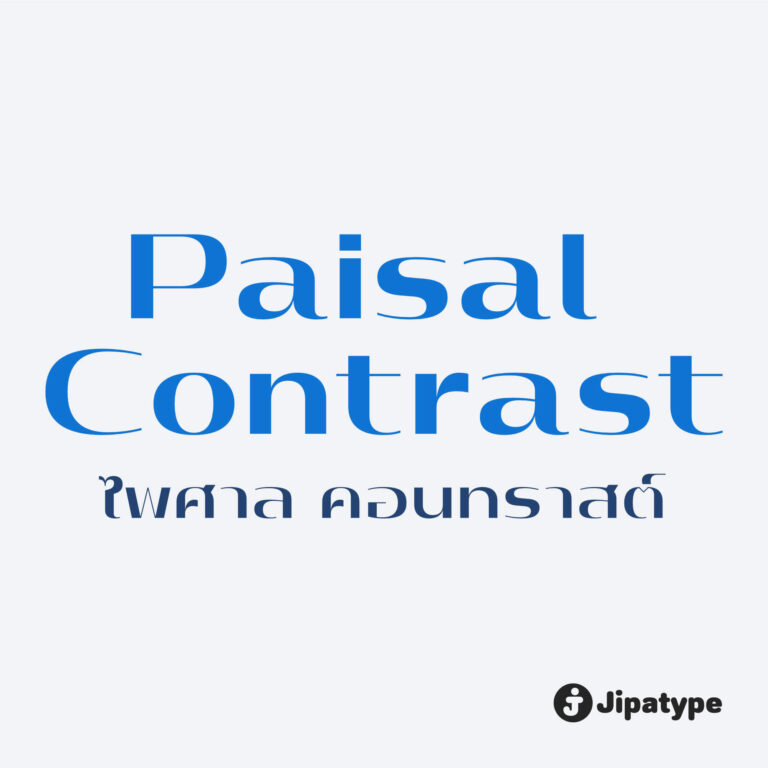
Chewatext Rounded เป็นแบบอักษรที่พัฒนาต่อมาจาก Chewatext มีรูปลักษณ์กลมมน เรียบง่าย เรขาคณิต มีให้เลือกใช้ถึง 18 สไตล์ รองรับตัวอักษรลาติน 1 และอักษรไทย เหมาะสำหรับสิ่งพิมพ์ต่าง ๆ ทั้งออนไลน์และออฟไลน์ ออกแบบโดย : อานุภาพ ใจชำนาญ (Anupap Jaichumnan)สามารถทดลองใช้เวอร์ชันฟรีผ่านแอปฯ ของจิปาไทป์ได้ในเชิงพาณิชย์ ดูรายละเอียดและดาวน์โหลดแอปฯได้ที่ : jipatype.com
ปักษา เป็นแบบอักษรซานเซอริฟสำหรับตกแต่ง ชื่อของแบบอักษรนี้มาจากคำไทยที่แปลว่า “นก” ออกแบบโดย : อานุภาพ ใจชำนาญ (Anupap Jaichumnan)สามารถทดลองใช้เวอร์ชันฟรีผ่านแอปฯ ของจิปาไทป์ได้ในเชิงพาณิชย์ ดูรายละเอียดและดาวน์โหลดแอปฯได้ที่ : jipatype.com
วิจิตรา เป็นแบบอักษรเซอริฟแบบแคบคอนทราสต์สูง ชื่อของแบบอักษรนี้มาจากชื่อทั่วไปของผู้หญิงไทย ซื่งมีความหมายว่า ‘สวย’ หรือ ‘งดงาม’ ออกแบบโดย : อานุภาพ ใจชำนาญ (Anupap Jaichumnan)สามารถทดลองใช้เวอร์ชันฟรีผ่านแอปฯ ของจิปาไทป์ได้ในเชิงพาณิชย์ ดูรายละเอียดและดาวน์โหลดแอปฯได้ที่ : jipatype.com
Chewatext เป็นแบบอักษรซานเซอริฟที่มีรูปลักษณ์เรียบง่าย เรขาคณิต และเทคโนโลยี มีให้เลือกใช้ถึง 18 สไตล์ รองรับตัวอักษรละติน 1 และอักษรไทย ทำให้เป็นตัวเลือกที่ดีที่สุดสำหรับโปรเจกต์ร่วมสมัย ไม่ว่าจะเป็นงานสิ่งพิมพ์ต่าง ๆ ทั้งออนไลน์และออฟไลน์ ออกแบบโดย : อานุภาพ ใจชำนาญ (Anupap Jaichumnan)สามารถทดลองใช้เวอร์ชันฟรีผ่านแอปฯ ของจิปาไทป์ได้ในเชิงพาณิชย์ ดูรายละเอียดและดาวน์โหลดแอปฯได้ที่ : jipatype.com